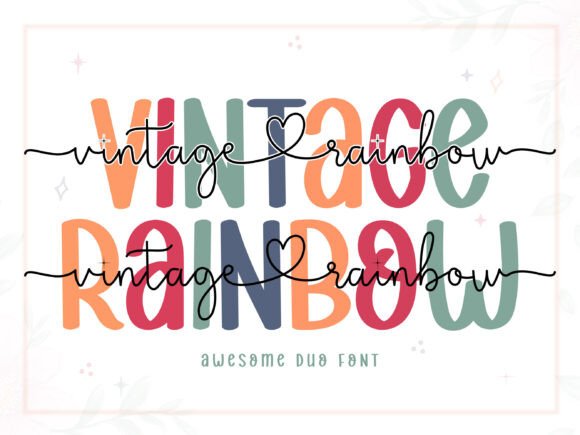
Vintage Rainbow
Vintage Rainbow: A Fonte Manuscrita que Transforma seus Projetos
Se você está em busca de uma tipografia que una romance e alegria, a Vintage Rainbow Duo é a escolha perfeita. Esta fonte manuscrita em estilo script traz um toque delicado e ao mesmo tempo vibrante, ideal para quem deseja destacar cartões, convites, headlines e artesanato com um visual chic e cheery.
- Design versátil: Funciona impecavelmente em cartões de felicitação, convites de casamento, capas de livros, posts de redes sociais e até em embalagens de produtos.
- Legibilidade suave: Apesar de seu estilo cursivo, a Vintage Rainbow mantém boa legibilidade, garantindo que mensagens importantes sejam facilmente compreendidas.
- Toque romântico: As curvas delicadas e os detalhes de escrita à mão conferem um ar de romance que eleva qualquer criação a um nível mais elegante.
Em resumo, a Vintage Rainbow Duo não é apenas uma fonte; é uma ferramenta de expressão criativa que adiciona cor, estilo e emoção aos seus projetos. Experimente agora e descubra como um toque de arco‑íris vintage pode transformar seu design em algo verdadeiramente inesquecível.